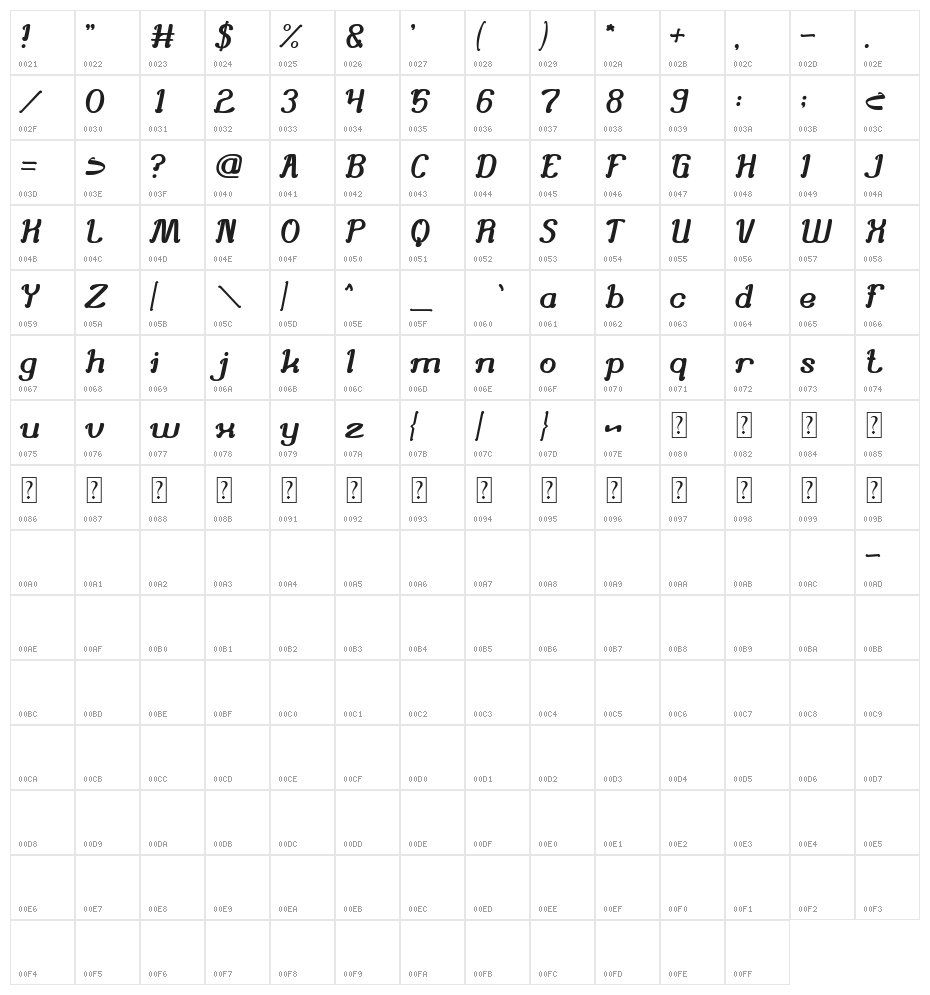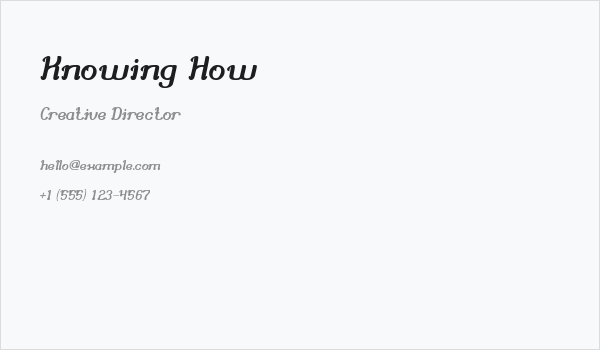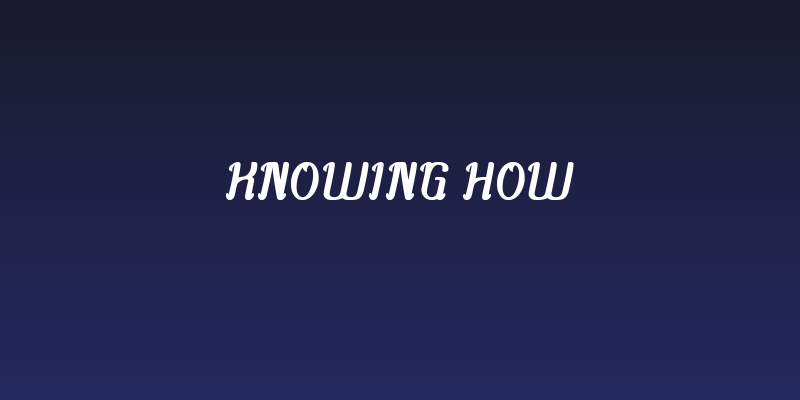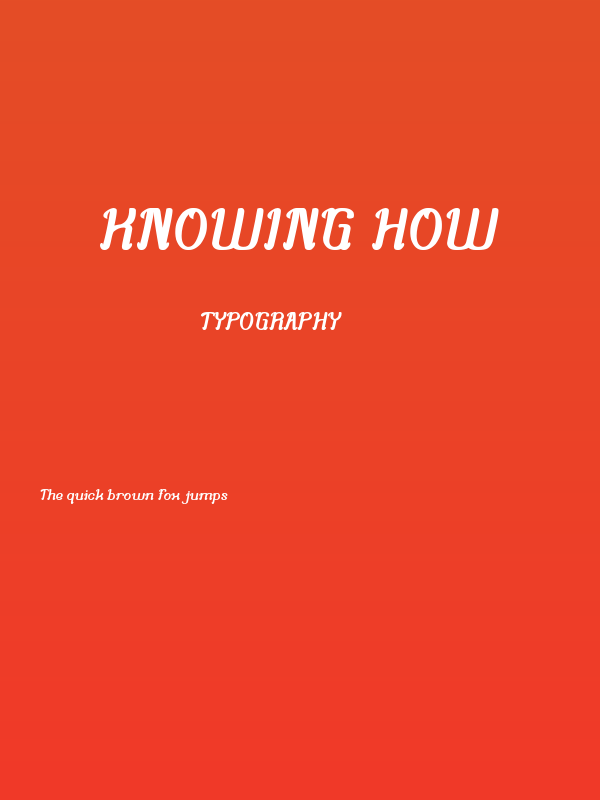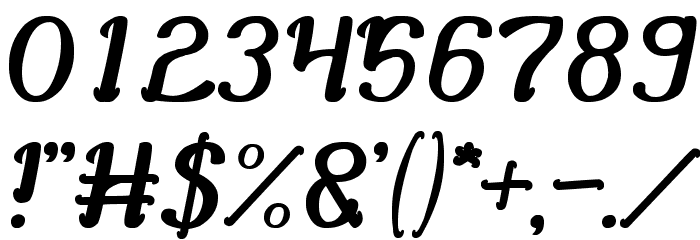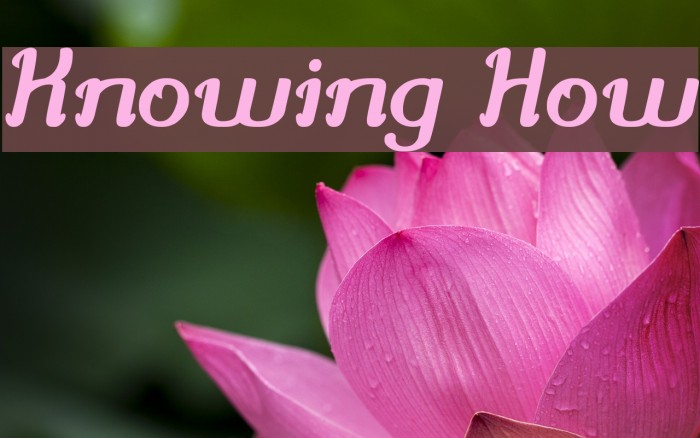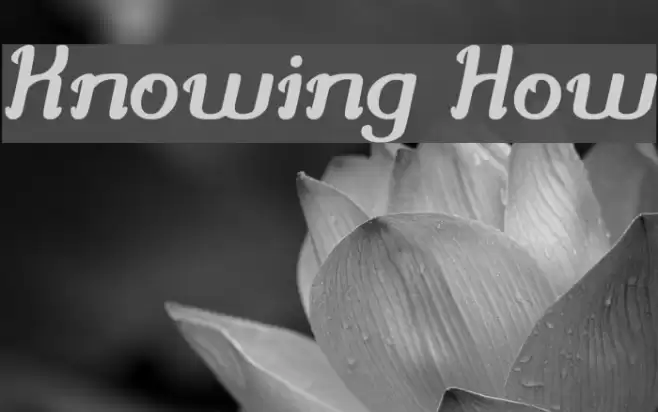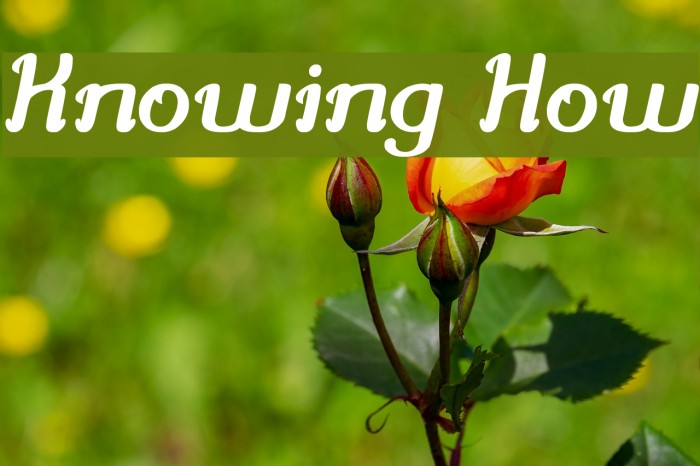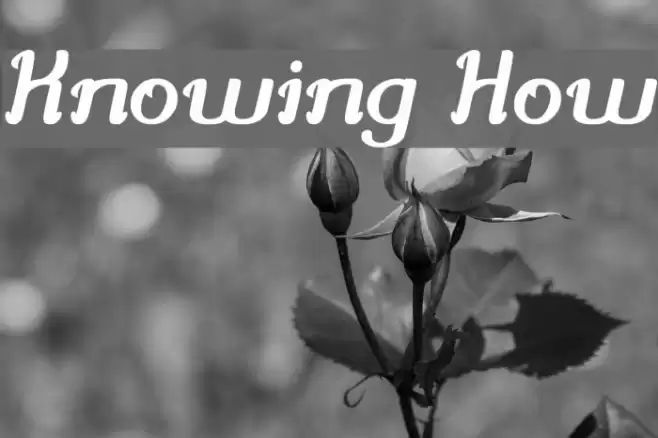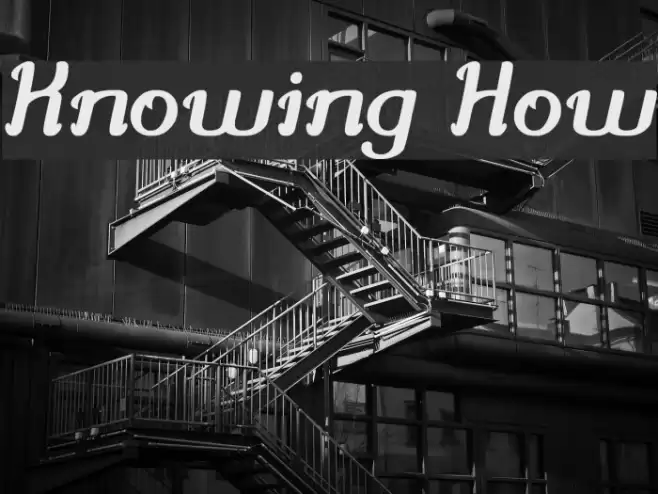
Knowing How Font
| Название | Knowing How |
| Общий стиль | Playful, Handwritten |
| Область применения | Headlines, Logos, Invitations |
| Рекомендуемые проекты | Ideal for invitations, greeting cards, branding, and personal projects. |
| Автор | Fonts by Dieter Steffmann |